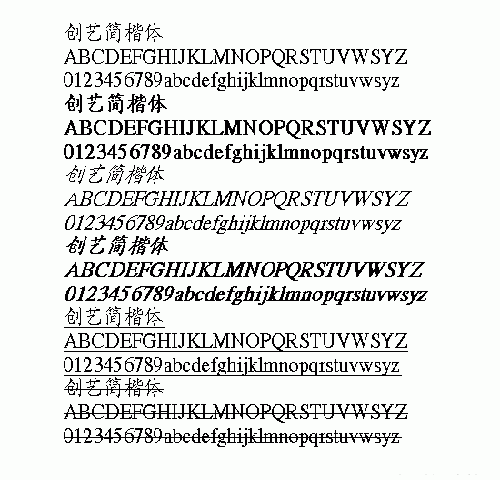
創(chuàng)藝簡(jiǎn)楷體字體是一個(gè)非常美觀的字體。具備了楷書字體所有特點(diǎn),同時(shí)又帶有藝術(shù)字體的特征??梢杂脕?lái)設(shè)計(jì)廣告等。兼容多種計(jì)算機(jī)操作系統(tǒng)!歡迎下載使用。
使用說(shuō)明楷書楷書也叫正楷、真書、正書。由隸書逐漸演變而來(lái),更趨簡(jiǎn)化,橫平豎直?!掇o海》解釋說(shuō)它“形體方正,筆畫平直,可作楷?!薄_@種漢字字體端正,就是現(xiàn)代通行的漢字手寫正體字。
楷書也是一種官名。《新唐書·百官志二》記中書省史館有楷書二十人,寫國(guó)史楷書十八人??瑫鳛楣倜卜Q作楷書手,掌繕寫之事,在同一機(jī)構(gòu)中并置,因具體分工有所不同。《通典·職官二十二》記楷書手為流外勛品官。宋代無(wú)楷書手之稱,惟稱楷書。